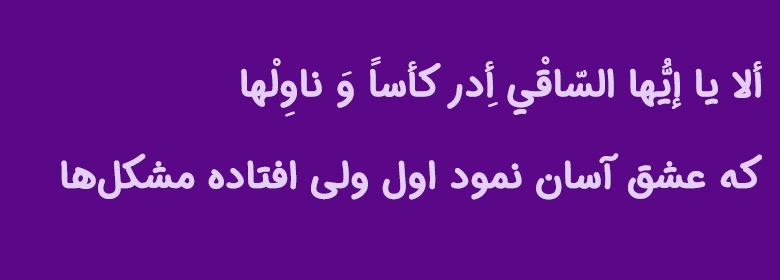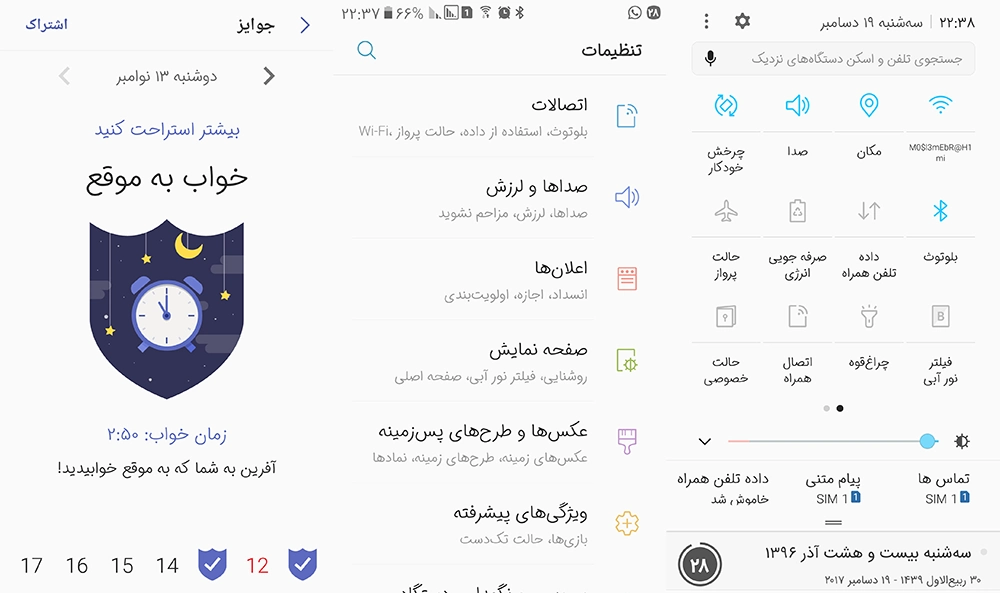
فونت ایران سنس دستنویس (IranSans-dn)
فونت ایران سنس دست نویس همانطور که از نامش مشخص است نسخهای با بازطراحی در قالب قلم دستنویس از فونت ایران سنس است که توسط مسلم ابراهیمی در سبک نسخ و ساختاری دوستانه برای استفاده در متنهای طولانی، فونت موبایل، وب فونت و حتی تبلیغات طراحی شده است.
این فونت با طراحی کاملا نزدیک به فونت ایرانسنس ساخته شده است که شکل حروف صمیمی تر، نرمتر و دوستانهتر بوده و دارای منحنیهای بیشتری در دندانهها و حروف میباشد. همچنین نقاط در این فونت به طور پیشفرض چسبان طراحی شده که در نقاط سهتایی جدا از هم هستند.
در ادامه این نوشته از سایت فونتچی به نقد و بررسی کامل فونت دستنویس ایرانسنس خواهیم پرداخت؛ فونتی که میتوانید از آن در متون کوتاه تا بلند استفاده کنید که برای استفاده در تبلیغات نیز مناسب هستند.
ایرانسنس دست نویس با استایل گرد (Rounded) طراحی شده تا شخصیتی نرم و سیالتر داشته باشد. اغلب حروف در این قلم شکل کاملا متفاوتی با فونت ایرانسنس دارند.
سبک طراحی و وزن فونت ایران سنس دستنویس
حس دیدن و خواندن یک دست خط مطمئناً برای شما متفاوت از متنی است که بهوسیله فونت تایپ شده است. در دستخط، حرکات دست نویسنده را درک میکنید و حروفی را میبینید که بصورت بداهه بر روی کاغذ شکل گرفته است.
فونتهای ماشینی هرگز نمیتواند این ادراک انسانی را منتقل کند اما به هر صورت ما روز به روز بیشتر وابسته تکنولوژی شدیم و به همین سرعت کمتر از قلم و کاغذ برای نوشتن استفاده کردیم. تا جایی که حتی نوشتههای غیر رسمی و شخصیامان را نیز با فونت تایپ کردیم. فونتهای سبک دستنویس برای جبران این کمبود طراحی میشوند و به همین دلایل نیز طرفداران زیادی دارند.
پشتیبانی از زبان فارسی و عربی
فونت فارسی ایران سنس دست نویس از دو زبان عربی و انگلیسی نیز پشتیبانی میکند. پشتیبانی این فونت از زبانهایی مثل عربی که دارای رسم خط فارسی هستند کامل بوده و شامل اعراب و برخی کاراکترهای خاص نیز میباشد.
شاید تنها ایرادی که بتوان به نسخه عربی گرفت این باشد که اعداد «۴۵۶» که در عربی تایپ متفاوتی نسبت به فارسی «۴۵۶» دارند، هنوز پیادهسازی نشده است.
در نسخه انگلیسی این فونت نسخه دستنویس اختصاصی درنظر نگرفته شده و از فونت دیگری وام گرفته شده است. چرا که هدف از این فونت ساختار دست نویس برای یک فونت فارسی بوده است. اما به هر صورت این کار صورت گرفته تا برای متون لاتین نیازی به تغییر قلم نداشته باشید.
پشتیبانی از اعداد فارسی هک شده
اعداد فارسی در این فونت به صورت مشترک برای زبان عربی نیز قابل استفاده هستند. اما به منظور اینکه از این فونت در توسعه سایت یا هدف تبلیغات استفاده کنید، نسخههایی هم در نظر گرفته شده که اعداد متفاوتی هستند.
مناسب برای فونت موبایل
اگر به دنبال یک فونت دست نویس برای موبایل هستید، این قلم میتواند بهترین گزینه باشد. ساختار دوستانه این فونت استفاده از موبایل را برای شما صمیمیتر خواهد کرد که میتوان در استوریهای اینستاگرامی و تصاویری که ایجاد میکنید بهره ببرید.
در تصویر بالا استفاده از این فونت را در موبایل مشاهده میکنید که در خوانایی بهتر متون به شما کمک خواهد کرد. چرا که روزانه همه ما با گوشی خود در ارسال پیام از طریق پیامرسانها سروکار داریم که انتخاب یک فونت مناسب جزو چیزهای ضروری است.
نسخههای WOFF و WOFF2 قلم ایران سنس دست نویس برای استفاده در وب ساخته شدهاند. اگر دارای یک وبلاگ یا سایت شخصی هستید، استفاده از این فونت میتواند ارتباط صمیمیتری را بین شما و بازدیدکنندگانتان ایجاد کند.
خوانایی این فونت مخصوص متن برای استفاده در وب عالی است که از وزن Bold آن میتوانید در عناوین، تیترها، نقل قولها و کادرهای رنگی استفاده کنید تا روی جملات و بخشهای کلیدی محتوا تاکید بیشتری داشته باشید.
علاوه بر این ساختار دست نویس این فونت برای سایتها و اپلیکیشنهایی که در حوزه کودک و نوجوان فعالیت دارند یک مزیت بهحساب میآید که در ایجاد ارتباط صمیمیتر با چنین مخاطبانی نسبت به سایر فونتها قویتر عمل کرده است.
انتظار میرود که در آینده شاهد ارائه وزنهای بالاتر برای این فونت و همچنین نسخه متغیر برای استفاده در سایتها باشیم تا اثرپذیری بیشتری از این فونت را در بین فونتهای دستنویس ببینیم.